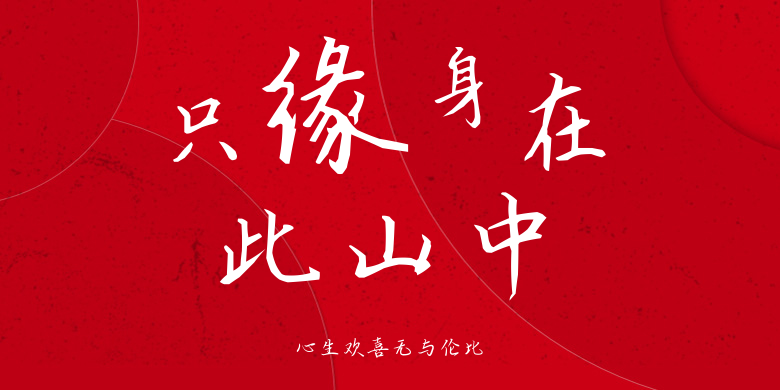
心生欢喜无与伦比
心生欢喜无与伦比,这款字体结构工整、笔画清晰,兼顾美观与易读性,适用于标题、正文、海报、包装、LOGO 等多种场景。字形优雅稳定,风格百搭耐看,适配日常排版与创意设计,让文字呈现更舒适、更具质感。心生欢喜无与伦比一笔一画,皆是细节,以均衡的比例、流畅的线条打造舒适视觉体验,字形端正大气,风格简约现代。无论是商业设计、品牌宣传还是日常排版,都能轻松驾驭,让文字更有格调与力量。心生欢喜无与伦比字体下载。